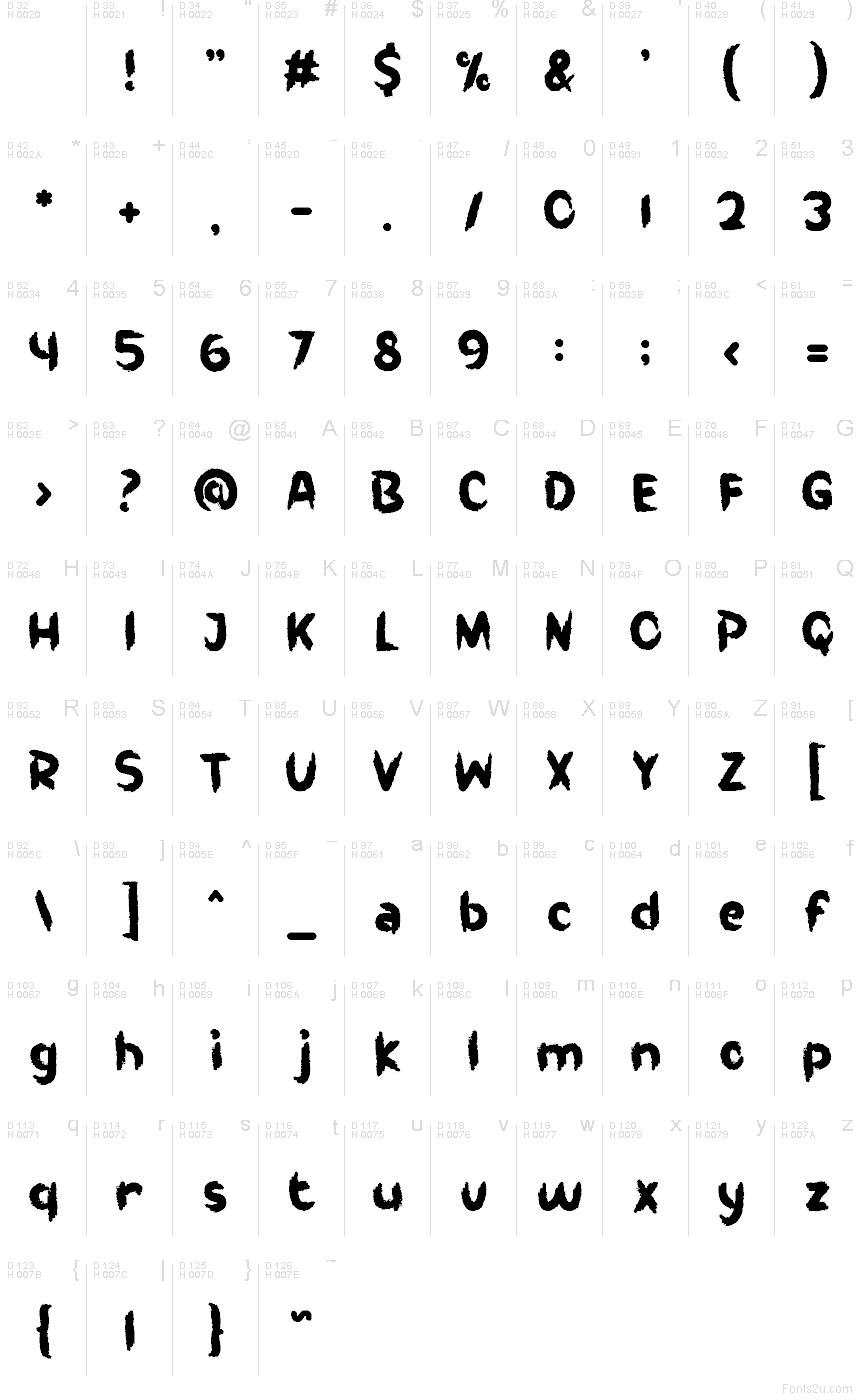
Crayon Craft Seven
Crayon Craft Seven od Putracetol Studio je bezplatné písmo v štýle kresby pastelkou, ktoré definujú drsné, práškové okraje a mäkké, zaoblené tvary. Textúra pôsobí, akoby bola priamo vrytá do písmen, čo im dodáva surový, ručne kreslený rytmus, namiesto úhľadných ťahov typických pre uhladené štetcové fonty.
Vďaka tomuto zrnitému povrchu sa skvele hodí na remeselné obaly, školské plagáty, obálky detských kníh, titulky do albumov alebo branding handmade produktov. Najmä krátke nadpisy ťažia z nepravidelných obrysov, ktoré dodávajú etiketám a grafikám na sociálne siete kreatívny, neformálny nádych bez toho, aby písmo pôsobilo ako lacná dekorácia.